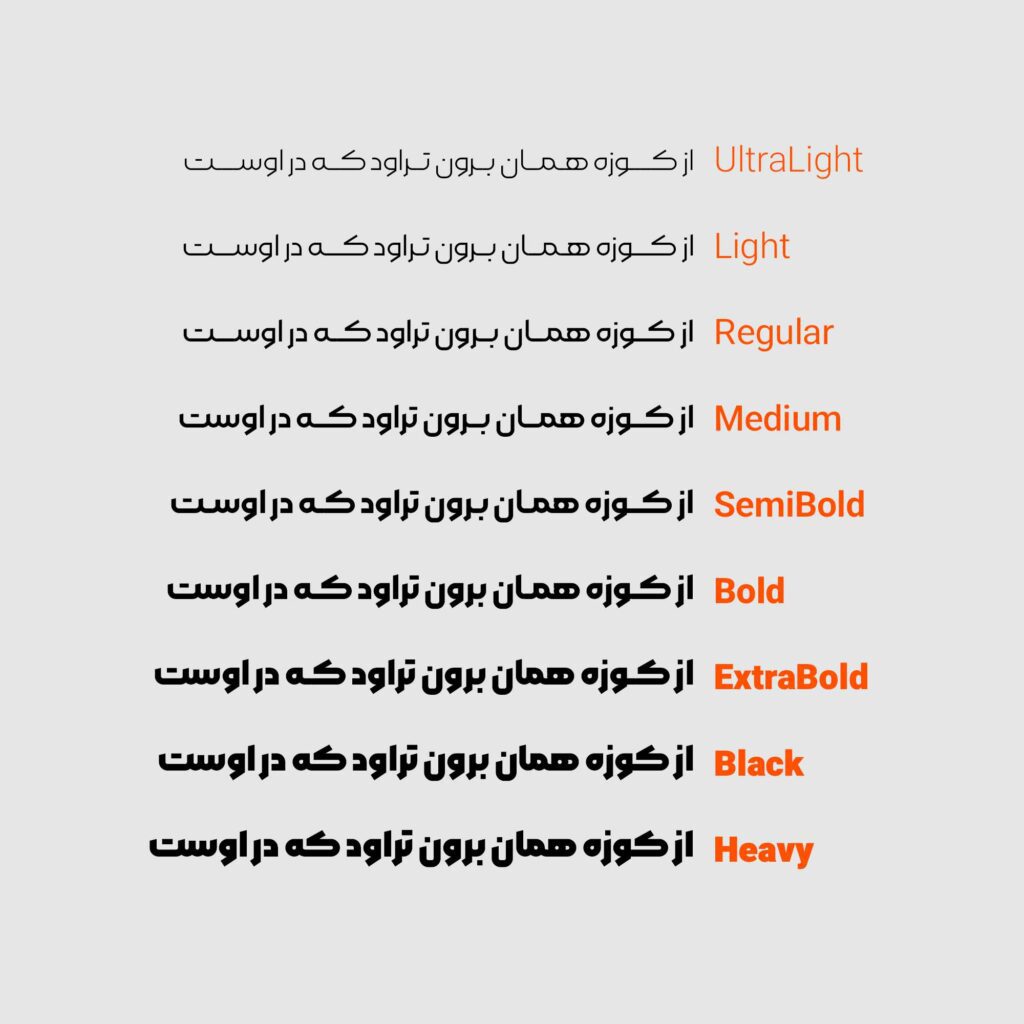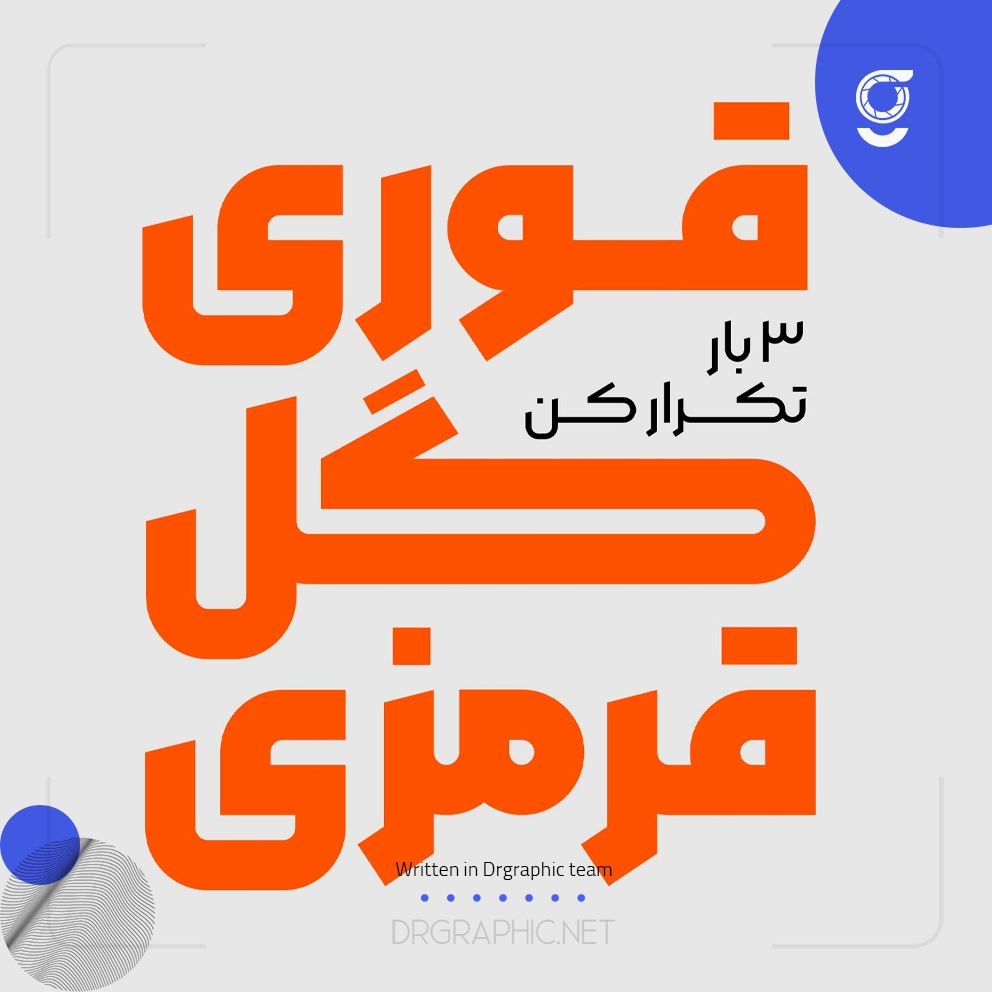
فونت مربع از نوع هندسی است که ریشه در خط کوفی بنایی دارد. با دکترگرافیک همراه باشید.
با اینکه سال هاست کوفی بنایی نقش مهمی در لوگوتایپهای فارسی ایفا میکند ولی جایگاه آن در فونت فارسی همچنان کمرنگ است.
فونت مربع برای کلمات و عبارات کوتاه طراحی شده و بیشتر مناسب موضوعات تجاری و مدرن است از قبیل طراحی وردمارک، اسلاید و کاورهای شبکههای اجتماعی و تبلیغات و بسته بندی.
در طراحی حروف فونت مربع، نسبت فضای مثبت به فضای منفی رعایت شده و کِرو ها دقیقا با محیط دایره همراستا شدهاند. در سنگینترین وزن نسبت فضای مثبت به منفی ۲ به ۱ و در سبک ترین وزن ۵ به ۱ است.